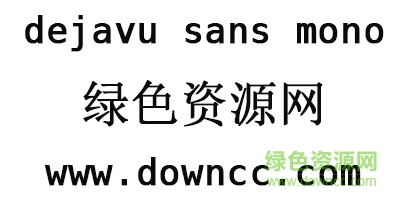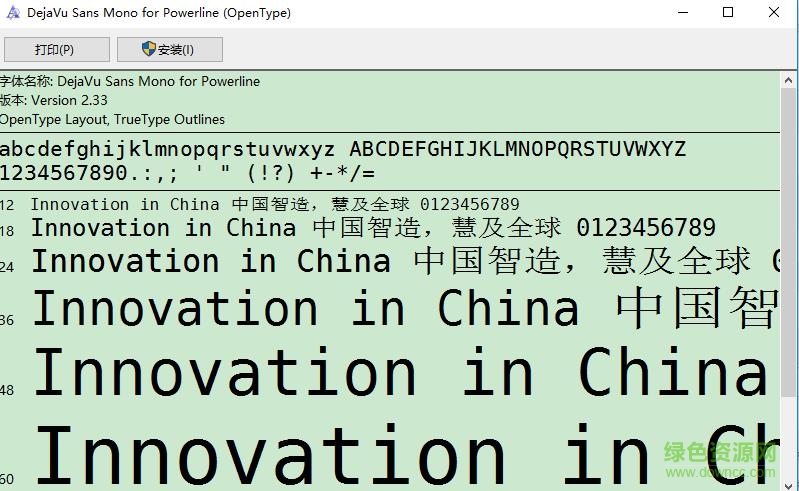
dejavu sans mono是一款常用的英文字體,這款字體字形端正大方,筆畫粗細(xì)均勻,實(shí)用性強(qiáng),廣泛應(yīng)用于包裝設(shè)計(jì)、雜志期刊、名片設(shè)計(jì)等領(lǐng)域,歡迎大家來(lái)綠色資源網(wǎng)免費(fèi)下載體驗(yàn)!
dejavu sans mono字體適用于名片設(shè)計(jì)、新聞媒體、宣傳海報(bào)、ppt、影視制作等領(lǐng)域,綠色資源網(wǎng)為您提供免費(fèi)下載使用!